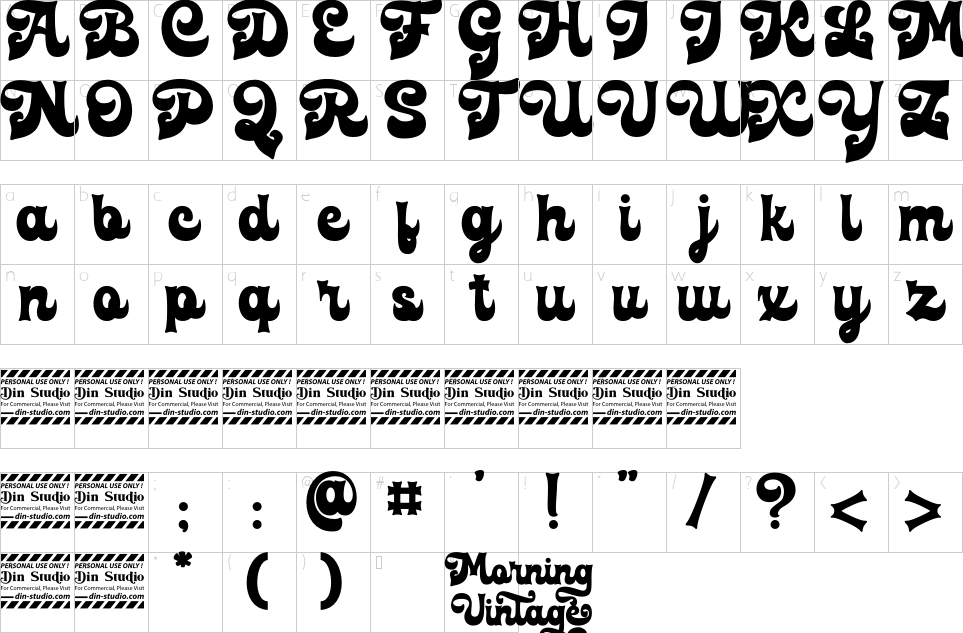
Descubra Morning Vintage Font, uma elegante e sofisticada fonte que se tornará sua aliada ideal para projetos de texto gráfico. Esta fonte vintage foi cuidadosamente criada pela Din Studio e oferece uma aparência clássica que combina perfeitamente com designs que valorizam a simplicidade e a elegância dos anos 1900. Se você está procurando por uma fonte para incorporar em projetos gráficos modernos, essa fonte certamente se encaixa perfeitamente. Com seu design atraente e versátil, é perfeita para headlines, descrições, e para qualquer tipo de layout que busque um toque único e memorável. Não deixe de experimentar Morning Vintage Font, um verdadeiro prazer para qualquer designer gráfico. Com um design elegante que remonta ao passado, esta fonte oferece uma escolha gratuita e prática para tornar seus trabalhos ainda mais criativos e sofisticados.